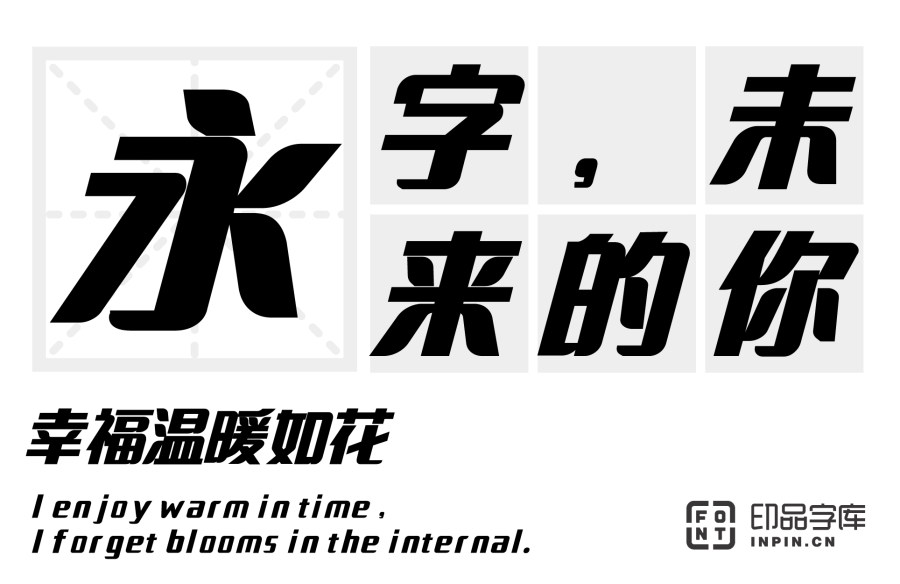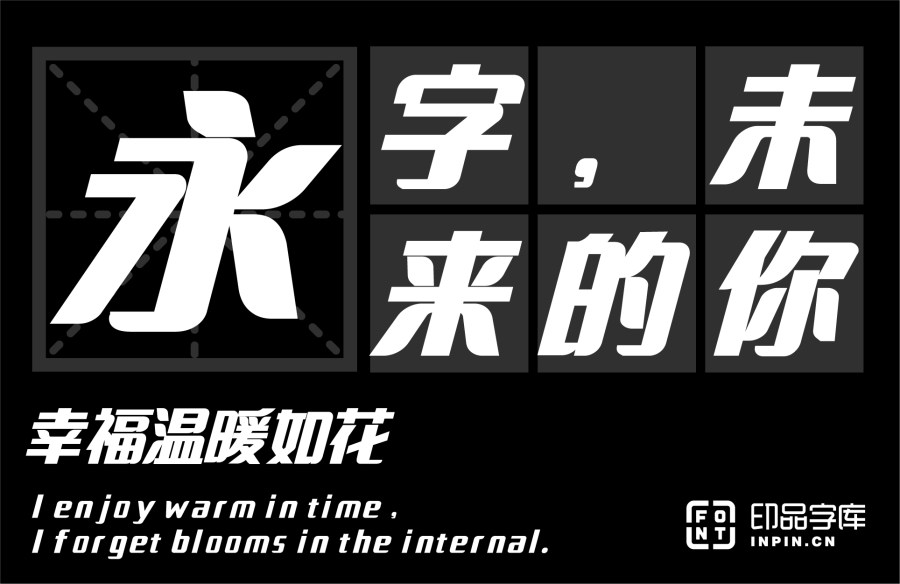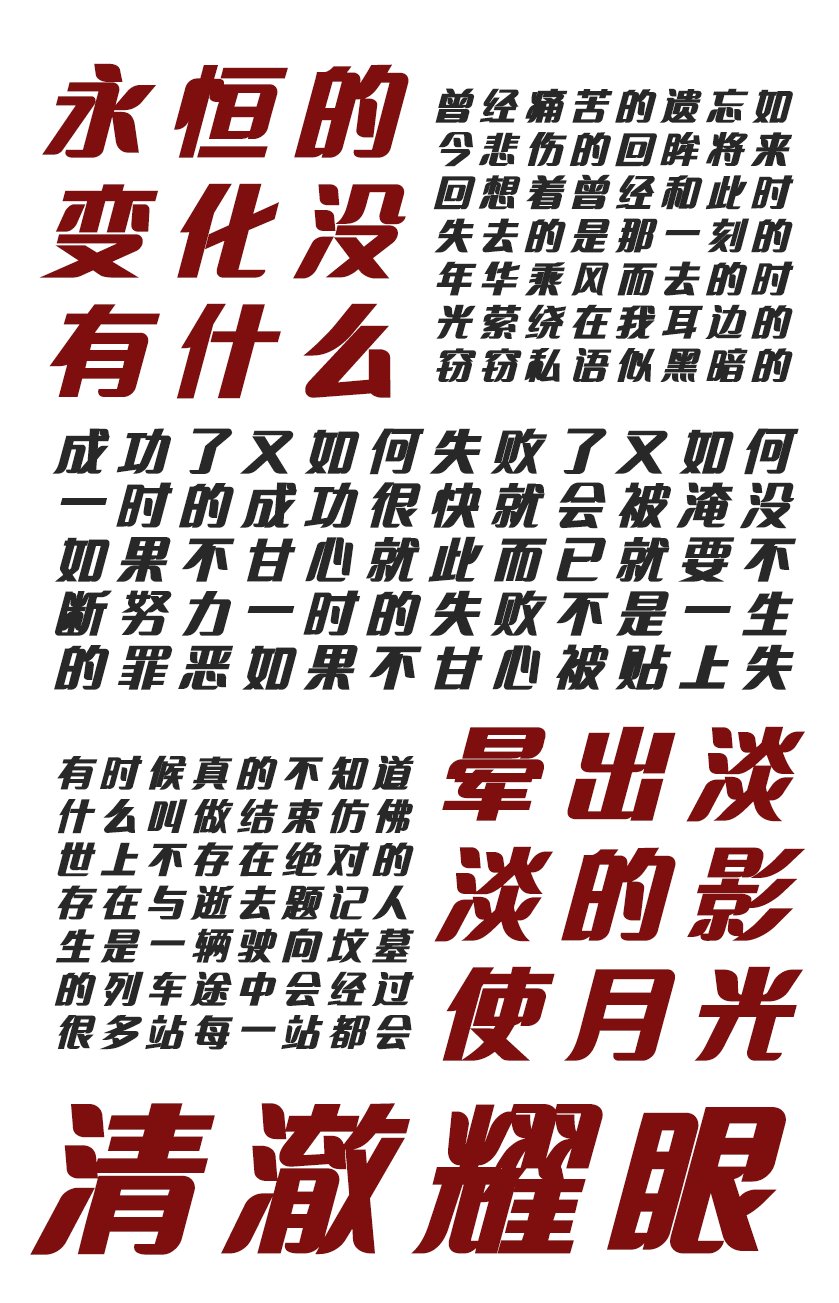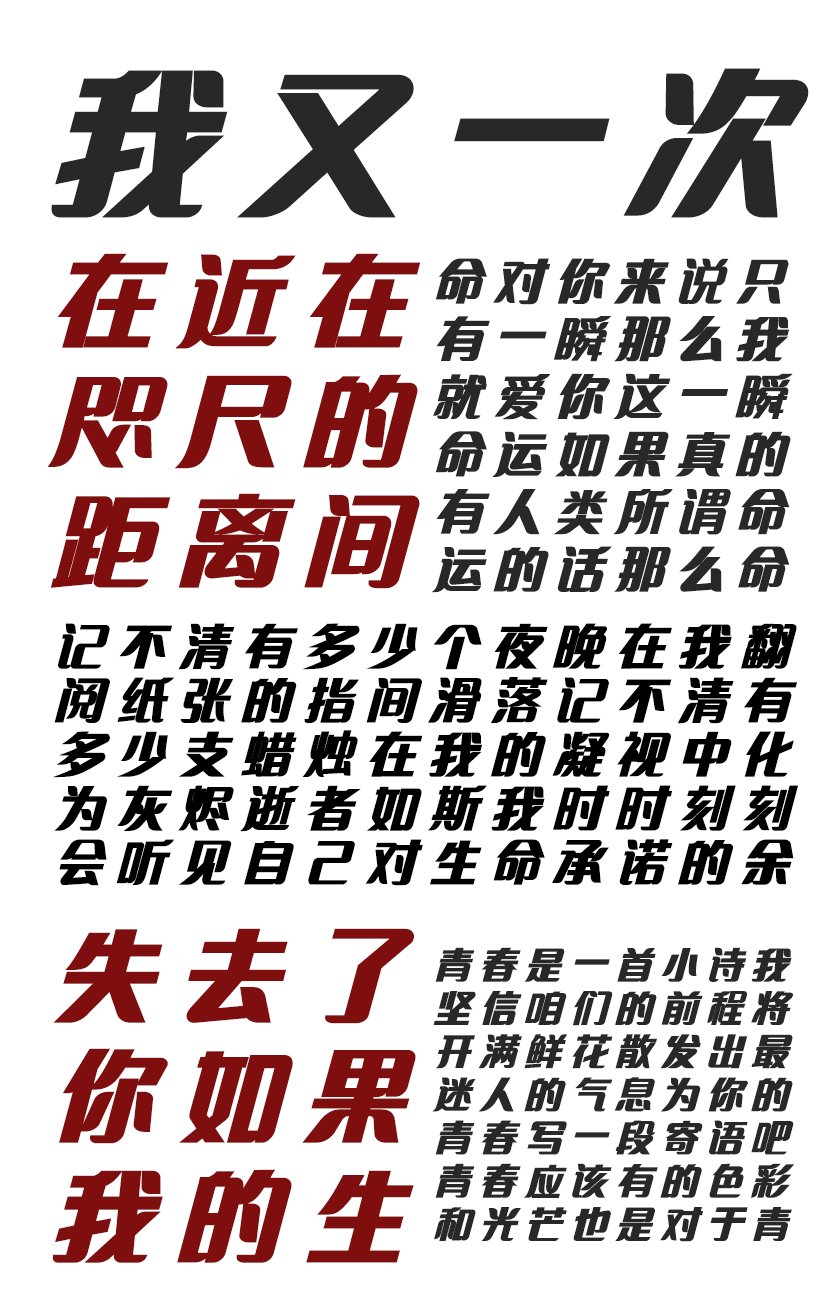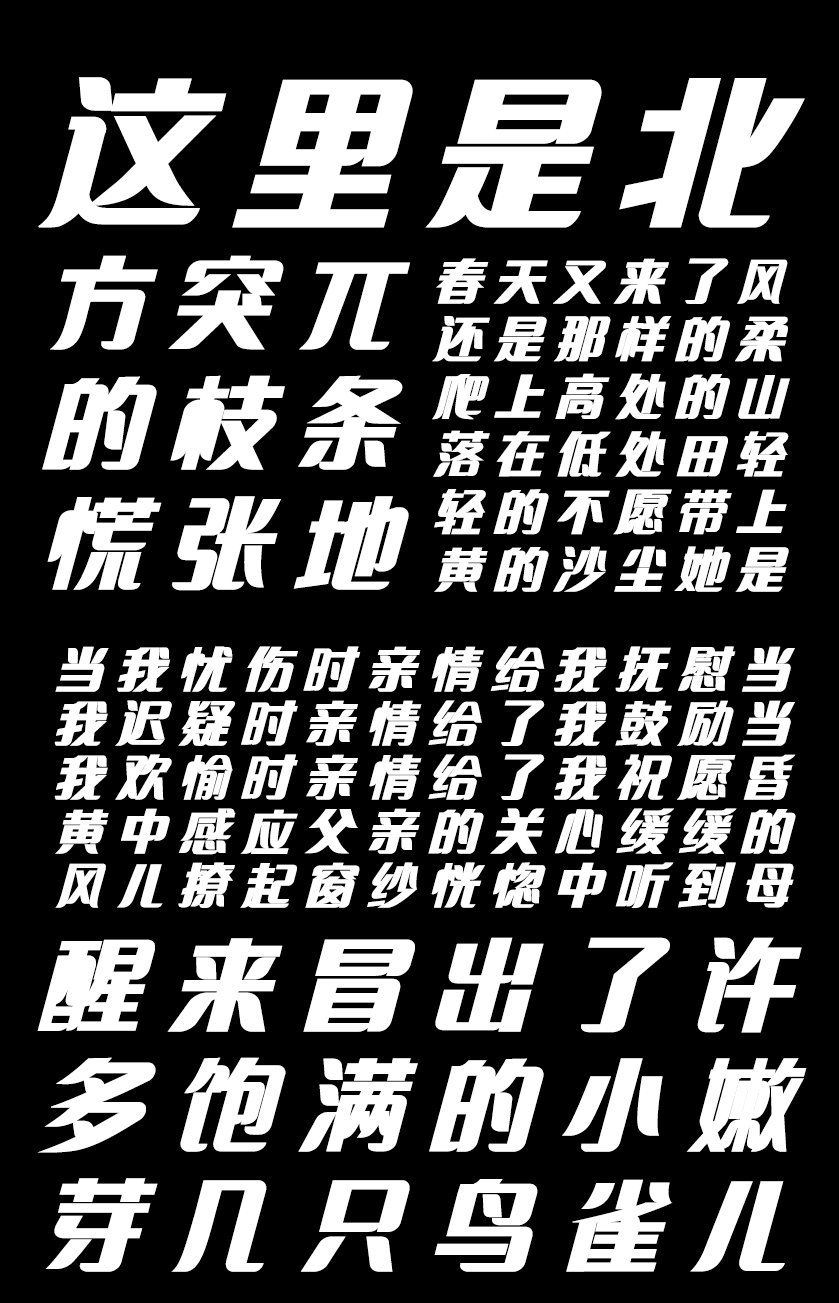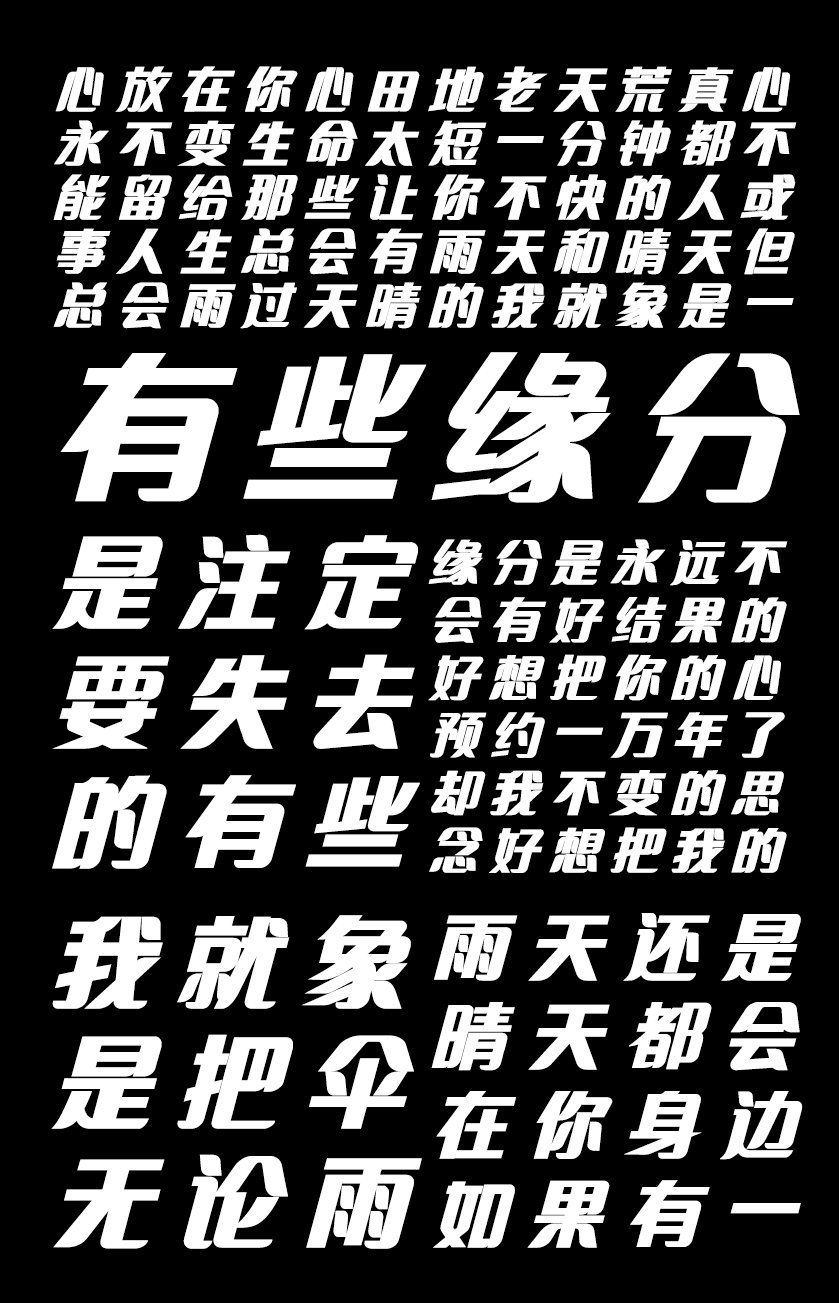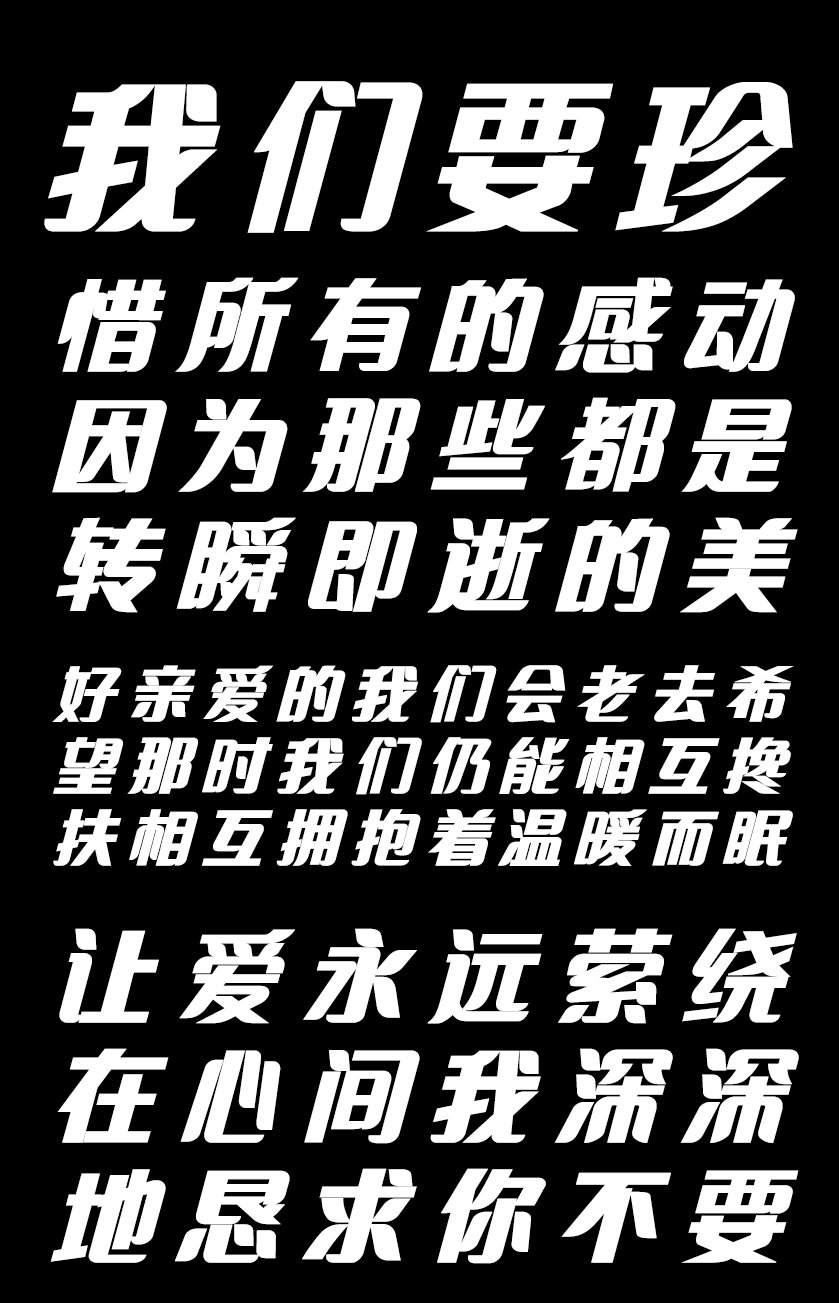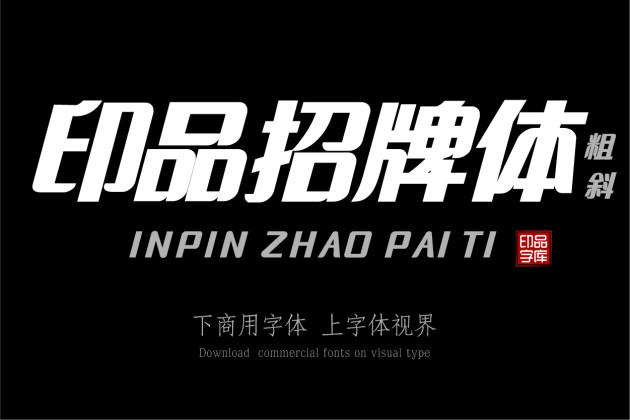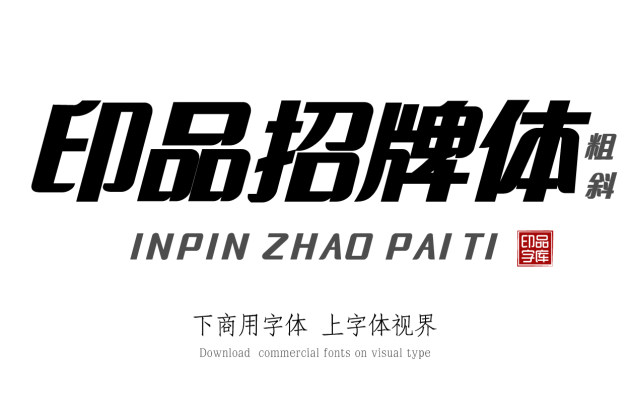
印品招牌体 粗斜
这款招牌体字笔画粗壮,略带有纤细笔触,字形紧聚,但不失美感。在弯钩处都作了一点线条处理,看起来不那么死板。它的一撇一捺像极了柳絮飘飘。即便放于手机中阅读也不会产生视觉突兀,给人以浑厚有力的感受 ! 分享到
印品招牌体,创作于2019年。是一款很适合招牌的字体,现已经被用于上海XX有限公司、上海XX股份有限公司等字体展示环境。
粗壮有力的黑体是被广泛使用的基本字体,不管是手机端还是电脑端基本上都是主流的屏显字体。
这款招牌体,相比于传统的黑体,更加圆润,让人感觉更加舒适。黑体字笔划整齐划一,它浑厚有力,朴素大方并且引人注目。
设计师在设计、做字过程中,做了一些细节调整优化。它的弯钩都作了一点线条处理,看起来不那么死板。它的一撇一捺像极了柳絮飘飘。这款字主要笔画粗壮,带有纤细笔触,字形紧聚,但不失美感。